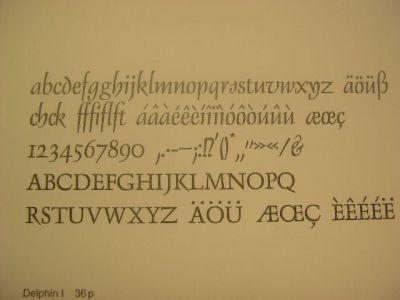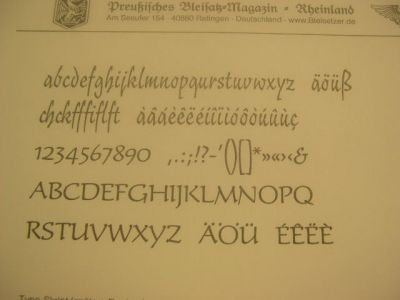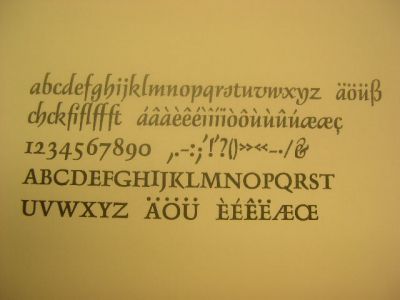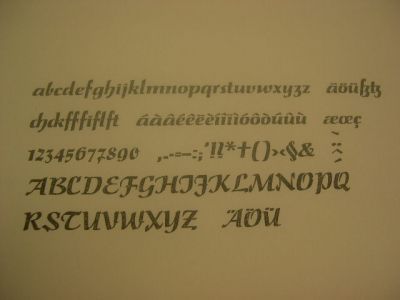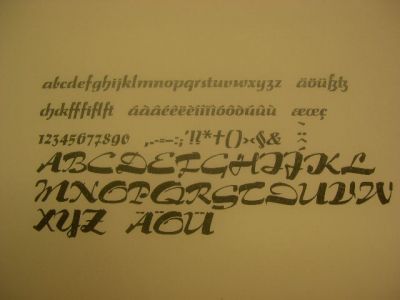
Welche Schriften sind das wohl?
Gerade einmal vier von insgesamt neun Aufgaben des Oster-Quizz 2006 zur Schriftenerkennung konnten bisher gelöst werden.
Dabei geht es darum, unbekannte Schriften zu klassifizieren:
Name, Schriftgießerei, Erstguß-Jahr, Künstler
Habt Ihr Lust, den Kollegen zu helfen?
Sagt Eure Meinung zu folgenden Schriften.
naja. ohne zu fighten und auf die schnelle,
bild nummer 1
sieht einer futura verdammt ähnlich, ich weiss
einige zeichen sind anders ('G'), aber vergleich das mal
mit deiner anderen futura, ich habe ja nur billige digitale
versionen hier. ;)
bild nummer 2
keine ahnung, interessantes 'ß'
bild nummer 3 geht wohl in die richtung 'craw' oder eher
'engravers roman'
bild nummer 4 und 5
keinen schimmer, sehen aber ebenfalls sehr interessant aus,
hast du nichtmal lust diese zu digitalisieren? ;)
naja. ohne zu fighten und auf die schnelle,
Das ist - natürlich - keine Futura. Die Futura ist meine Hausschrift.
vielleicht doch eine futura :twisted: :wink:
Unkommentiert zitiert:
No.4:
Noblesse, Bauer Hausschnitt 1908
bz. (lt. Seemann) J.John Söhne Hamburg, ohne Jahr.
Besonders das G und auch das E sind charakteristisch.
No.3:
Eine Mediäval Antiqua, sehr ähnlich ist die Renata von Krebs,
aber sie ist es nicht.
ich schliesse mich nur an...
zu Nr. 1 - Futura, soweit ich das an diesem Schriftmuster aus dem Web nachvollziehen kann. Meine digitalen Schriftschnitte der Futura sind ja schon deutlich "heutiger".
Interessant ist im Schriftmuster das Minuskel-g (Antiqua-g) in der Zeile
Radierungen zeitgemäßer Künstler
Das erstaunt mich, habe ich vorher noch nie gesehen - weiss hier jemand was?
Habe mir einige Zeit genommen, aber keine der Schriften finden können. Die beiden Groteskschriften (4&5) erscheinen mir sehr alt zu sein. So um 1900 oder sogar früher - die Ausführung mancher Details läßt auf ähnliche Schriften wie von Klinghardt oder Krebs aus dieser Zeit schließen.
Das Oster-Quizz ist jetzt beendet.
Alle Schriften sind bis auf eine Ausnahme ins Ebay eingestellt.
Einschließlich entsprechendem Vermerk über Sinn und Zweck der Versteigerung.
Die letzte Schrift, die Noblesse, muß ich nachher erst noch drucken. Dann kommt die auch ins Ebay.
Über das Ergebnis aller Auktionen (die letzte endet nächsten Sonntag) werde ich natürlich berichten.
Ich bedanke mich für die Teilnahme am Quizz.
ach, jetzt ist es doch eine futura? :evil: frechheit! ;)
ich denke die schrift basiert auf einer futura, man konnte einige
unterschiede zu einer 'echten' futura erkennen, aber ich habe nur
digitale versionen hier und will meine schriftmuster nicht raus-
graben, sonst kommt mir das regal wieder entgegen.
vielleicht ist ein ein klon oder ähnliches, soviel ich weiss wurde das
hier in der ehemailgen ddr getan, westliche schriften
Es sind eigene Fonts, richtig?
Wenn ich also z.B. Fonts von der Weiß-Antiqua will, dann brauche ich die Weiß-Antiqua Fonts:
- mager
- halbfett
- kursiv
etc.
Habe ich das richtig verstanden?
Richtig verstanden. Viele Programme z.B. Word werden einfach eine Schrift "fetter" machen oder schräg legen, wenn die entsprechenden Fonts fehlen. - Das reicht den meisten Nutzern aus. :-)
Jeder dieser Schnitte ist ein Font, der wie im Bleisatz extra berechnet wird. Oftmals gibt es sie auch im Paket günstiger.